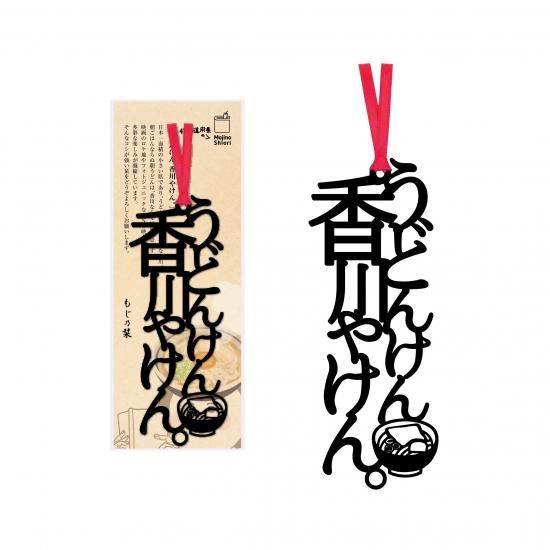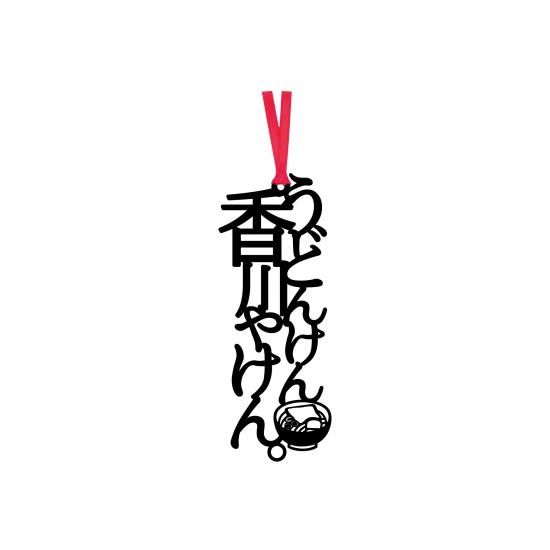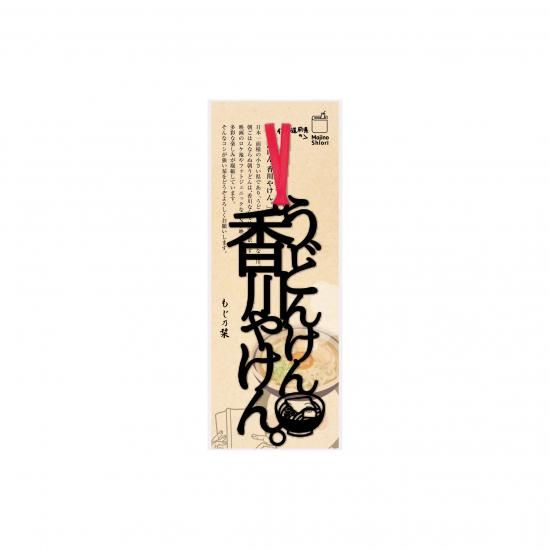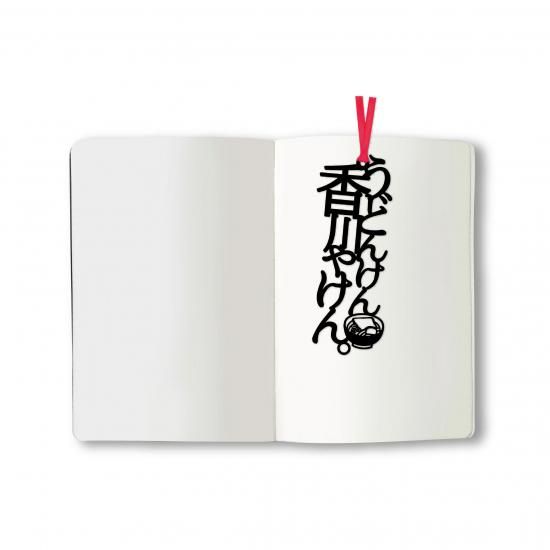
文字の47都道府県のしおり「うどんけん香川やけん。」
日本一面積の小さい県であり、うどん県として有名な香川。
朝ごはんならぬ朝うどんは、香川ならではの光景です。
映画のロケ地やフォトジェニックなSNS映えスポットも多く多彩な楽しみが凝縮しています。
そんなコシが強い栞をどうぞよろしくお願いします。
木材パルプや綿を原料とした環境素材を採用し、耐久性・耐水性に優れたファイバーの特徴を活かすことで、言葉がフォントごと切り取られたような巧緻で美しい『文字のしおり』のデザインが実現しています。